字由字体嵌入式合作介绍,已和剪映、小红书建立合作
什么是字由字体嵌入式合作?
嵌入式字体是指将字体文件以受控方式集成到数字产品(App、游戏、网站、电子书、设计工具、视频编辑软件等)的渲染管线中,使产品内的所有文字显示脱离对用户本地系统字体的依赖,实现跨设备、跨平台的一致呈现。
特别对于一站式设计软件、内容创作平台(如Canva可画、剪映、美图秀秀、小红书等),嵌入式字体是核心创作基础设施之一。 这类平台需要向海量创作者提供数百款字体,且必须确保每一款字体在商用场景下的合规性。字由嵌入式字体服务正是为此而生。
字体嵌入式合作案例
剪映字体嵌入案例
字由一次性提供了超过 128 款字体,包含标题、创意、手写、艺术字等多种风格,满足各类创作场景。
将这些字体内置到剪映软件中,用户在使用剪映制作的视频时,可以直接在软件中切换不同的字体,为视频选择最合适的字体。
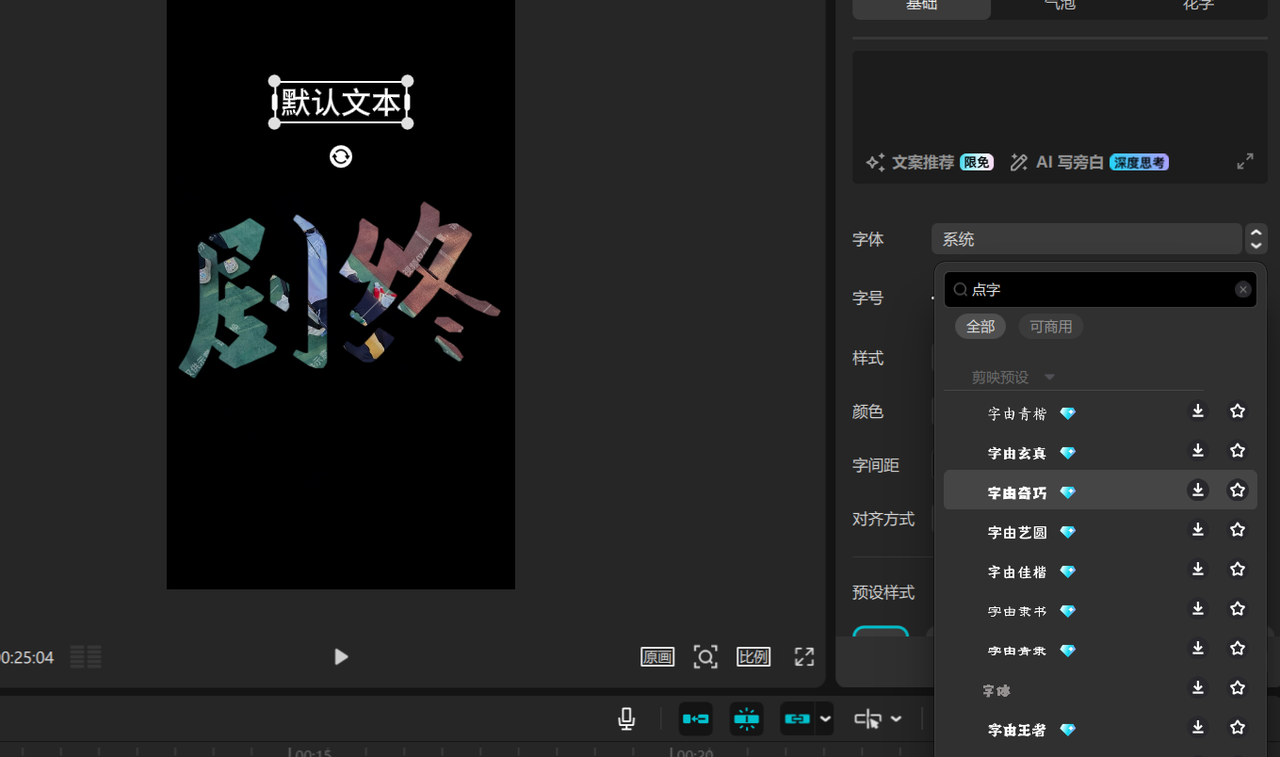
小红书字体嵌入案例
字由精心筛选并提供了多款契合平台“生活美学”、“真实分享”调性的字体入驻小红书。这些字体视觉上更具手写感、松弛感与亲和力,完美适配日常Vlog、好物笔记等内容形式,从视觉设计层面帮助用户和平台提升内容的质感与辨识度。
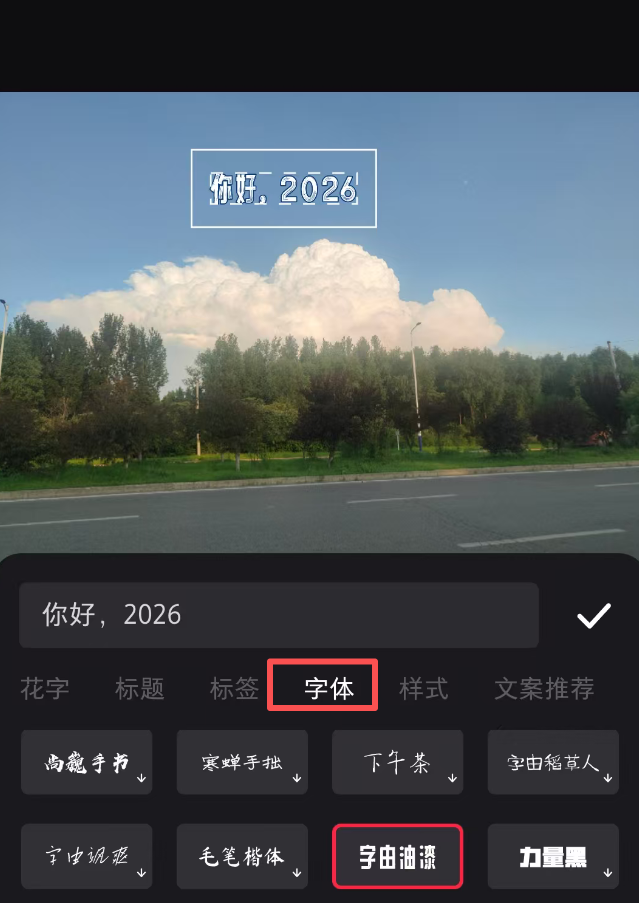
Canva 字体嵌入案例
字由字体嵌入方式比较简单,将字由丰富的原创字体打包,放到 Canva 的设计后台编辑器中,用户可以在设计的时候,进行字体的切换和使用。
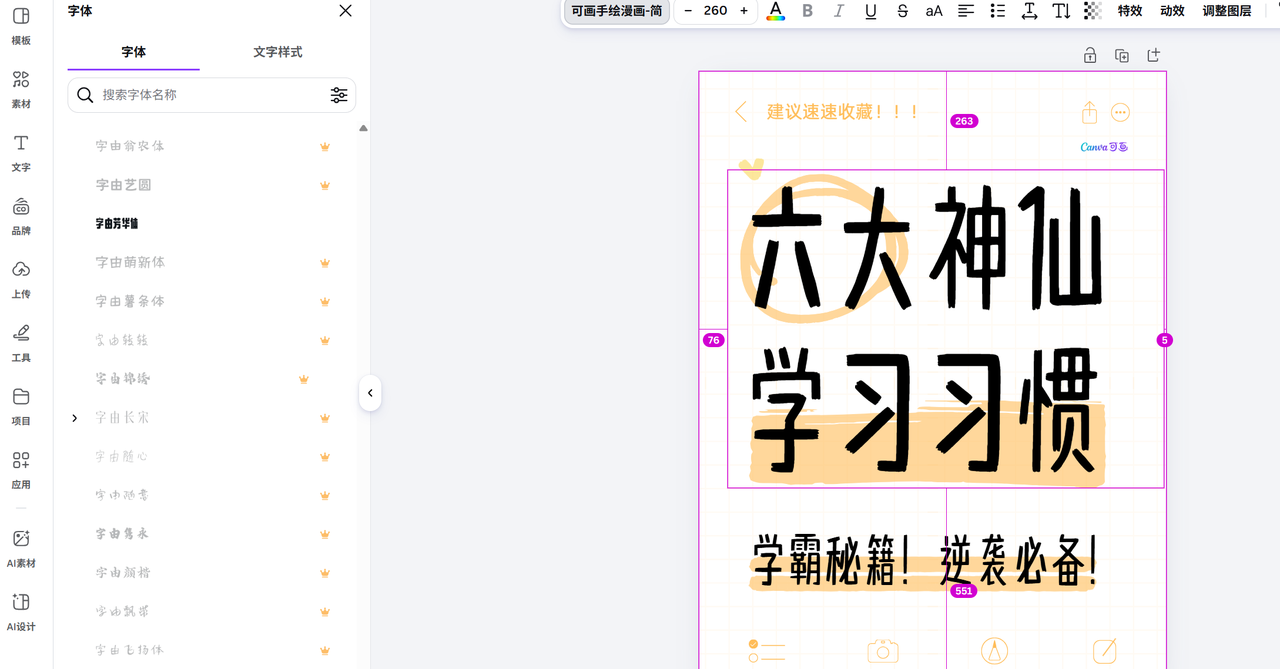
在Canva等在线设计平台,嵌入式字体库让用户在设计海报、社交媒体图片时,能直接调用高质量的正版字体,极大降低了普通用户的创作门槛与版权风险。
字体嵌入式的价值
降低创作门槛,提升效率:
平台内置海量字体库,将“寻找—下载—安装—使用”的传统流程压缩为“编辑器内一键应用”,彻底免除创作者的外部操作成本,使创作流畅度显著提升。
选择字由的原因
海量精选字体
5000+ 精选字体,灵活授权方式,满足多样设计需求,覆盖简繁中日韩及拉丁字符,支持定制开发,多语种场景无缝适配。